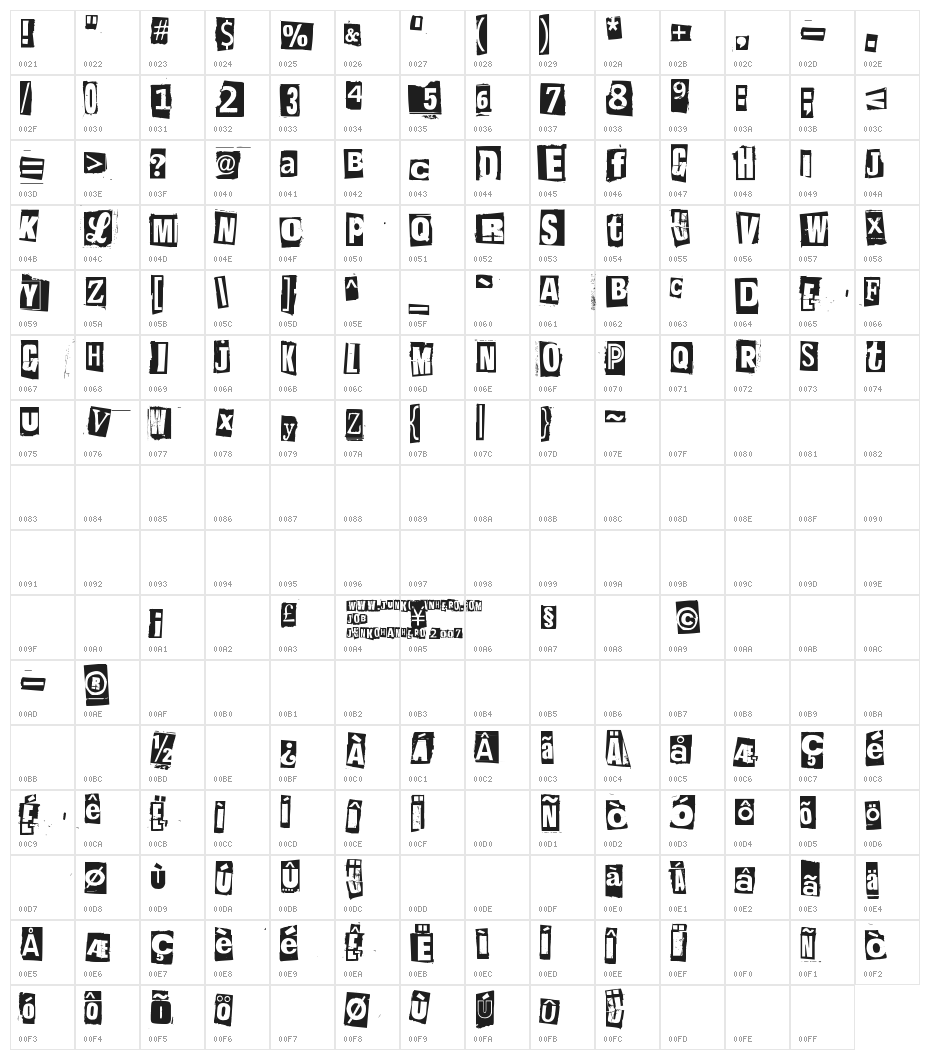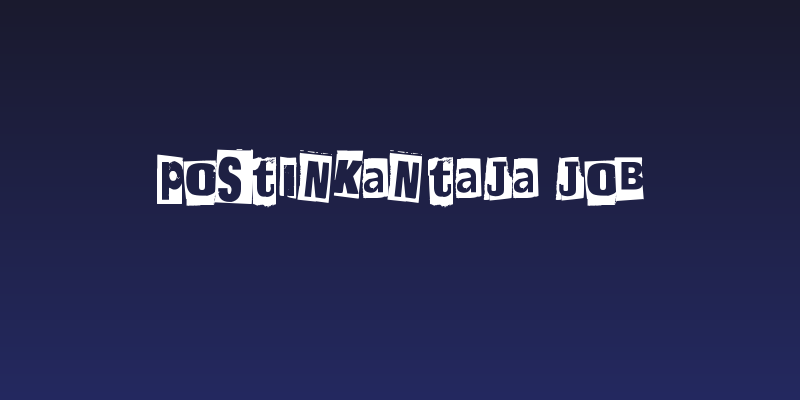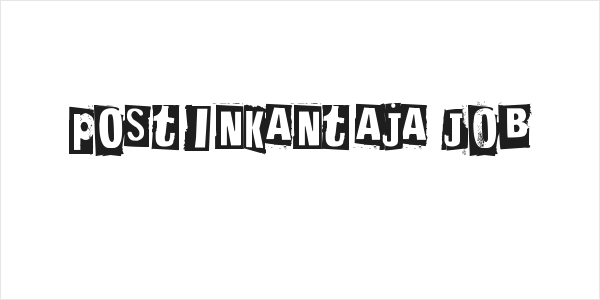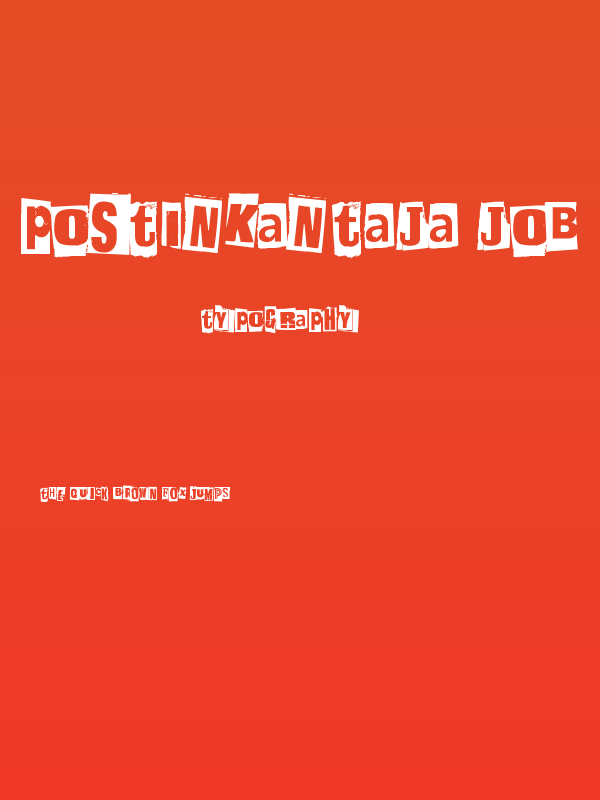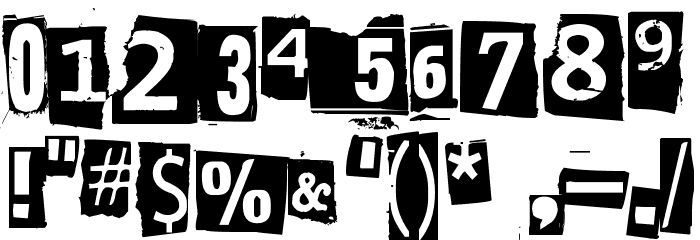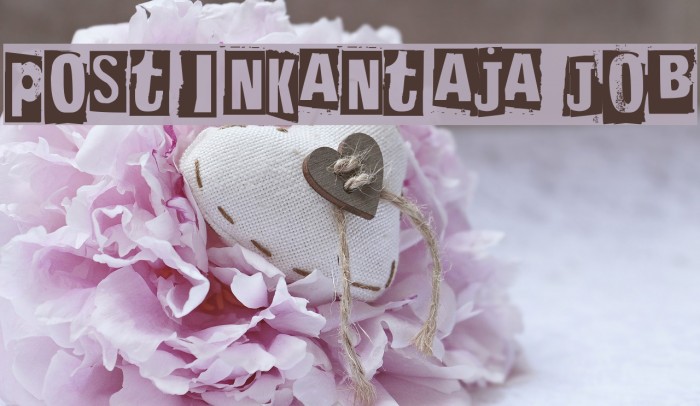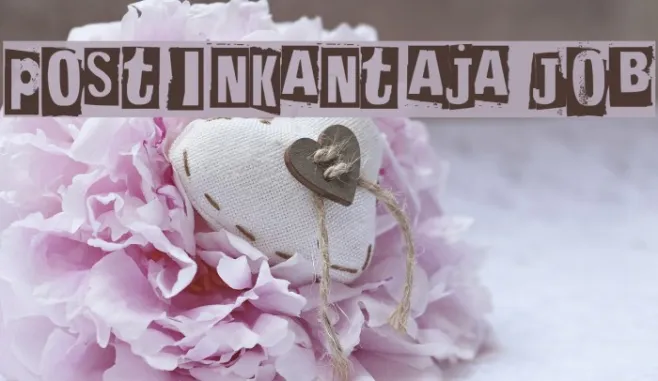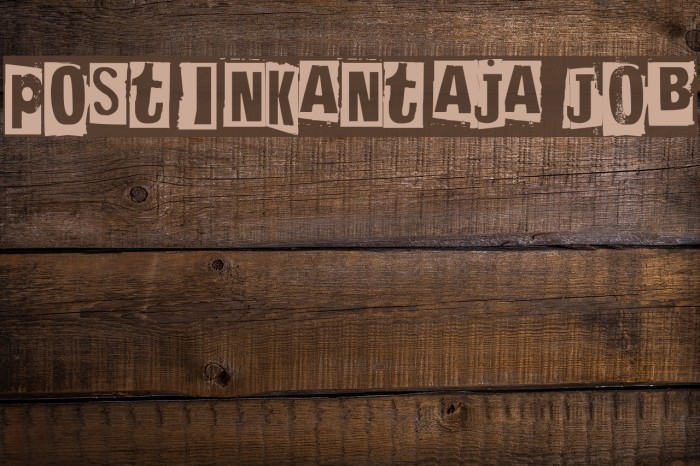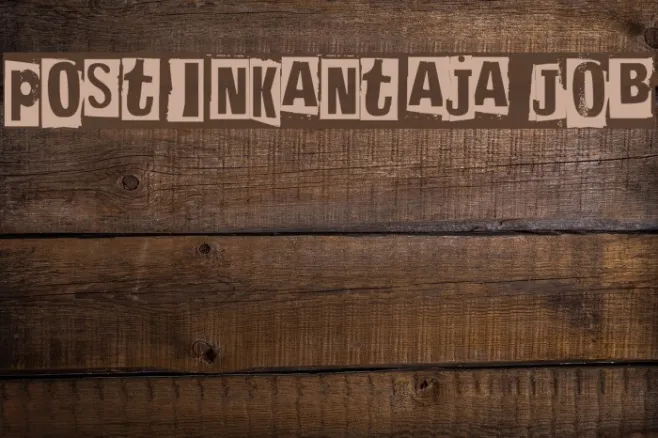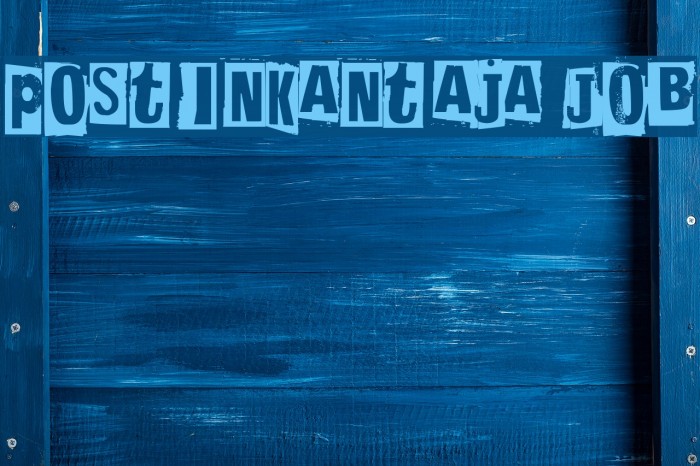
Postinkantaja Job Font
| Caso d'uso | Headlines, Posters, Album covers |
| Progetti proposti | Ideal for projects requiring a dramatic or rebellious tone, such as posters, album covers, or themed event invitations. |